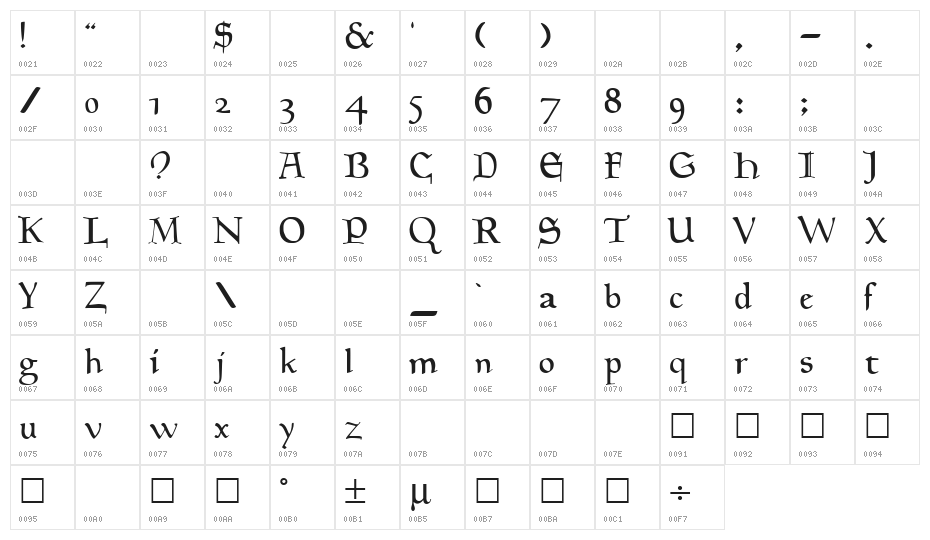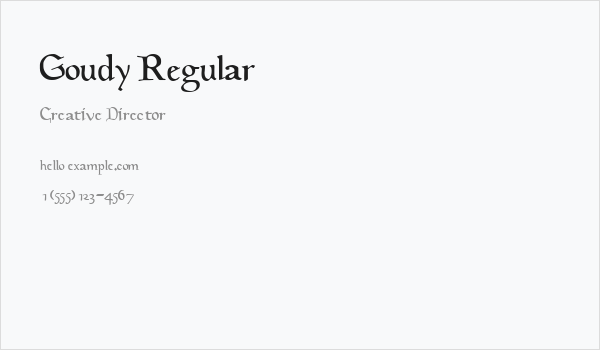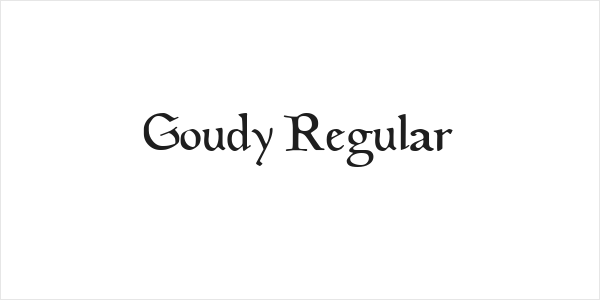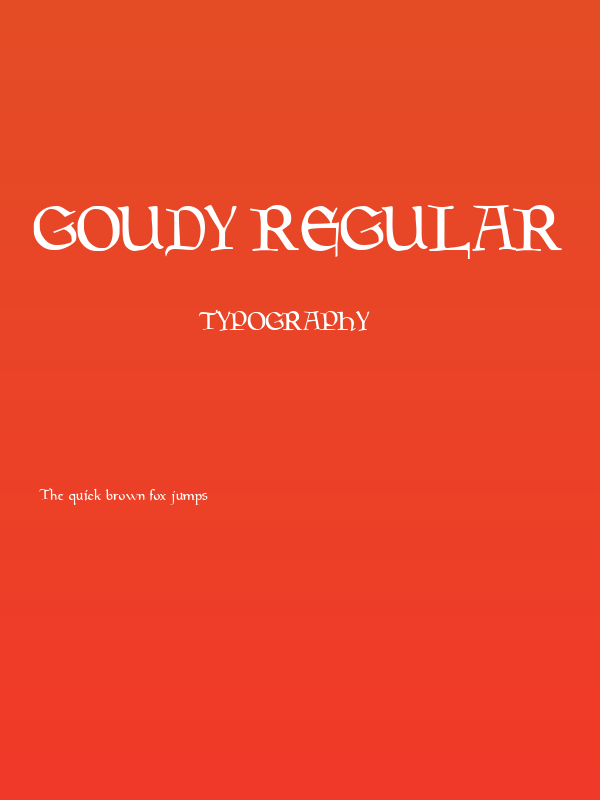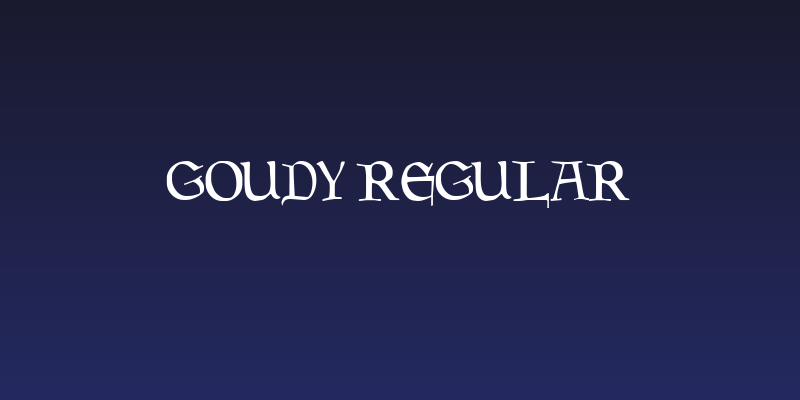
Goudy Regular Font
| النمط العام | Classic |
| حالة الاستخدام | Headlines, Logos, Invitations |
| مشاريع مقترحة | Ideal for projects requiring a touch of sophistication, such as wedding invitations, formal event programs, or luxury brand logos. |